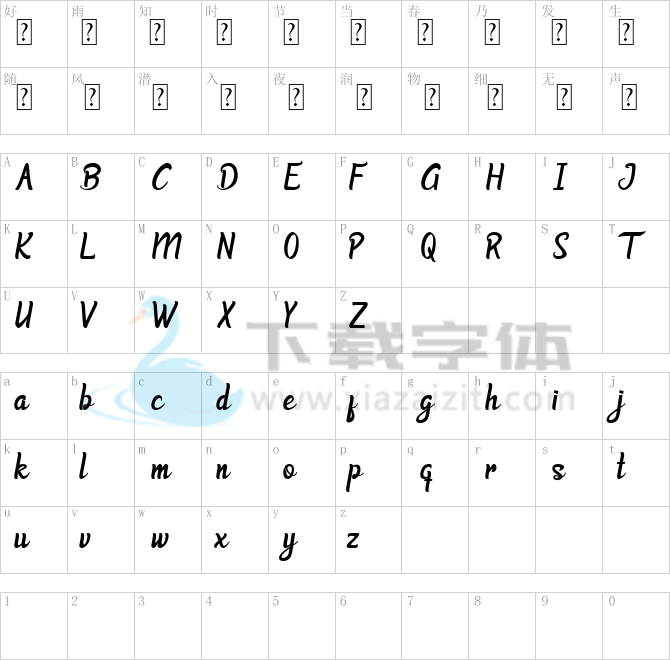
Athena.ttf字体下载
Athena.ttf字体下载,这款字体结构工整、笔画清晰,兼顾美观与易读性,适用于标题、正文、海报、包装、LOGO 等多种场景。字形优雅稳定,风格百搭耐看,适配日常排版与创意设计,让文字呈现更舒适、更具质感。Athena.ttf字体下载一笔一画,皆是细节,以均衡的比例、流畅的线条打造舒适视觉体验,字形端正大气,风格简约现代。无论是商业设计、品牌宣传还是日常排版,都能轻松驾驭,让文字更有格调与力量。Athena.ttf字体下载字体下载。